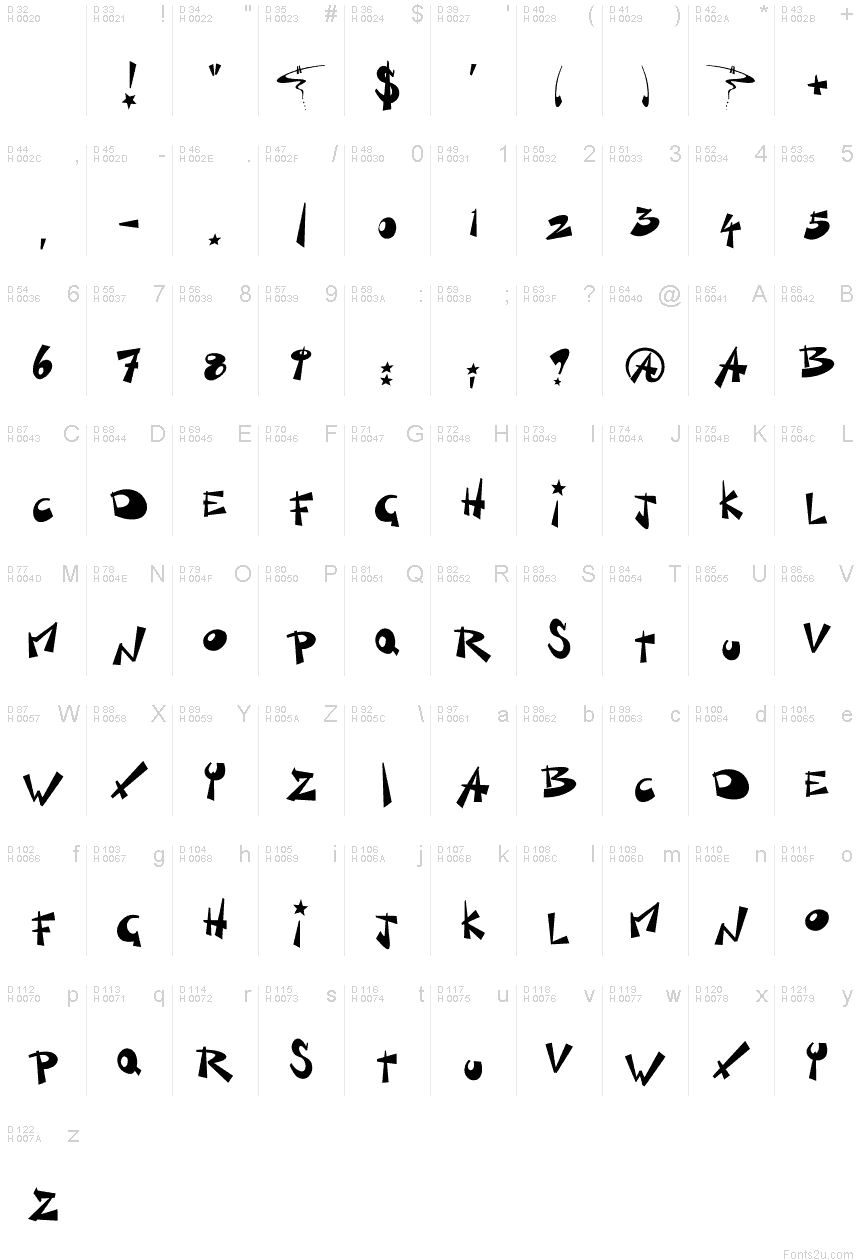
Kill Switch è un font display gratuito in stile fumetto che sembra assemblato con forbici e pennarello. Le lettere traballano e si inclinano, con forme spigolose e dettagli a stella che conferiscono a ogni parola un'energia disordinata e fatta a mano. È rumoroso, un po' folle e decisamente divertente: come una via di mezzo tra una richiesta di riscatto e un volantino punk.
Questo font gratuito spacca su poster di concerti, fanzine, titoli horror-comedy, copertine di album grunge, grafiche per skateboard e post audaci per i social. Usare Kill Switch in grandi dimensioni permette ai suoi bordi irregolari e al suo ritmo caotico di farsi notare davvero; abbinalo a un carattere sans serif pulito per il corpo del testo, così da mantenere la leggibilità mentre i titoli si scatenano.